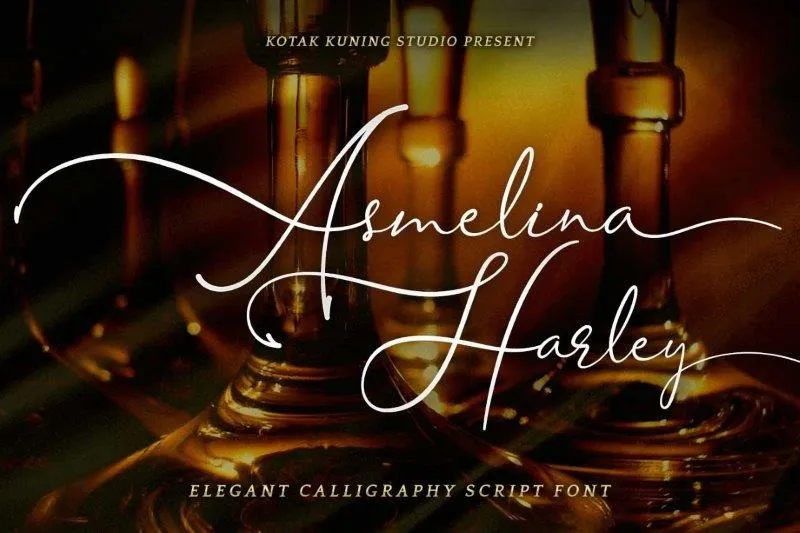
A Asmelina Harley Font é uma nova proposta no mundo dos tipos de letra, oferecendo uma assinatura única e com um toque de escrita. Este tipo especializado se destaca como a escolha perfeita para quem busca fazer declarações elegantes e sofisticadas em seus projetos. Os designers da 99designs criaram esta fonte script com detalhes que remetem à arte do traçado, tornando-a ideal para incorporar um toque de classe nos seus trabalhos gráficos. A Asmelina Harley possui uma variedade de ligaturas naturais em seu OpenType, permitindo criar efeitos visualmente próximos à escrita a lápis ou pincel. Esta font é perfeitamente ajustada para quem busca um elemento diferenciado e sofisticado em seus projetos. Suas linhas fluidas e elegantes se adaptam perfeitamente às mais variadas necessidades de design, oferecendo uma aparente naturalidade que transmite a sensação de escrita direta do papel. Com a Asmelina Harley Font, você pode criar designs simplesmente brilhando ou transformá-los em trabalhos artísticos e memoráveis. Esta é uma excelente opção para aqueles que buscam um design original sem comprometer a sua qualidade de impressão.